Shape of You Lettering. Calligraphic Ins
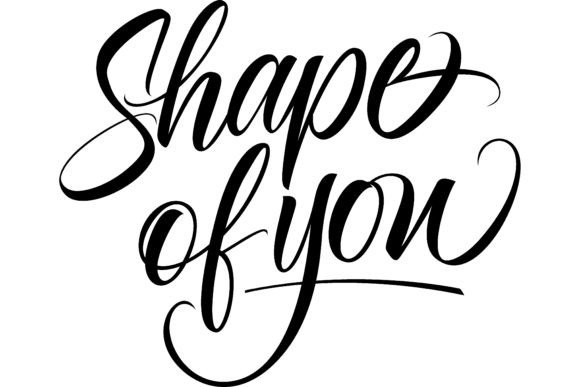
إذا كنت تبحث عن أصول عالية الجودة مثل Shape of You Lettering. Calligraphic Ins، فإن هذه الحزمة المميزة هي خيار رائع لمشاريعك الإبداعية.
سواء كنت تقوم بإنشاء منتجات الطباعة عند الطلب أو دعوات الزفاف أو رسومات وسائل التواصل الاجتماعي، فإن Shape of You Lettering. Calligraphic Ins هو الخيار المثالي.